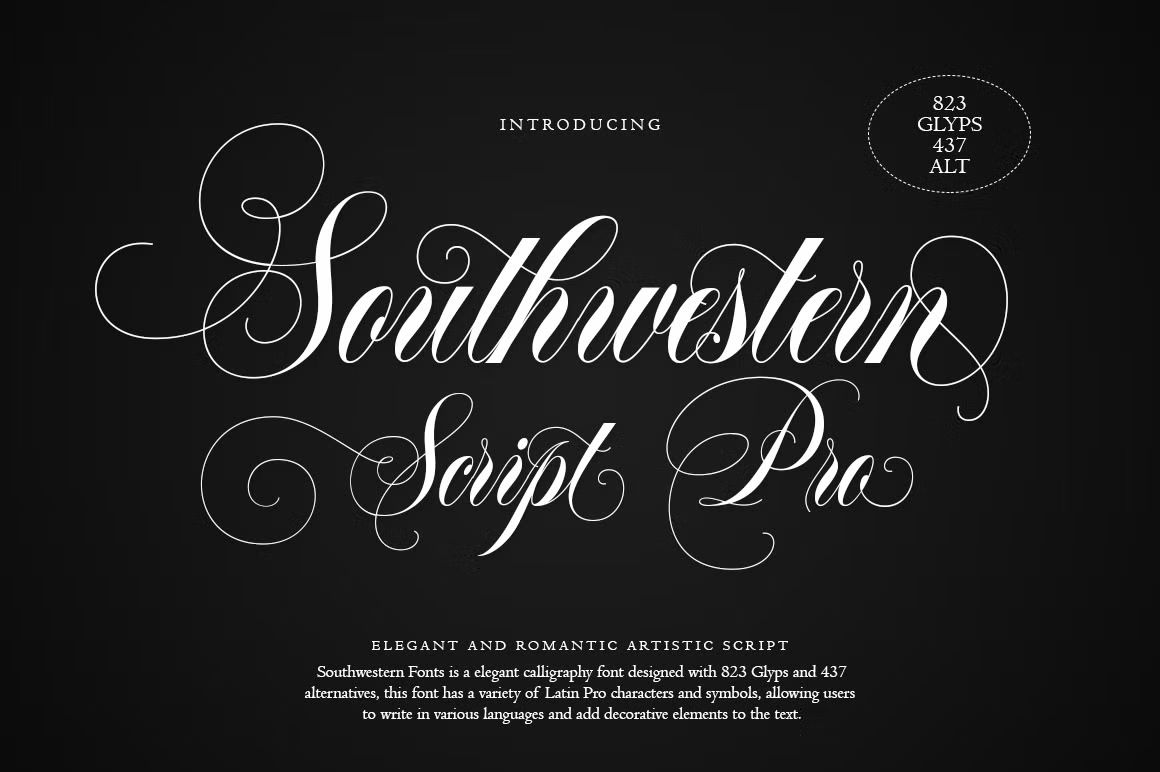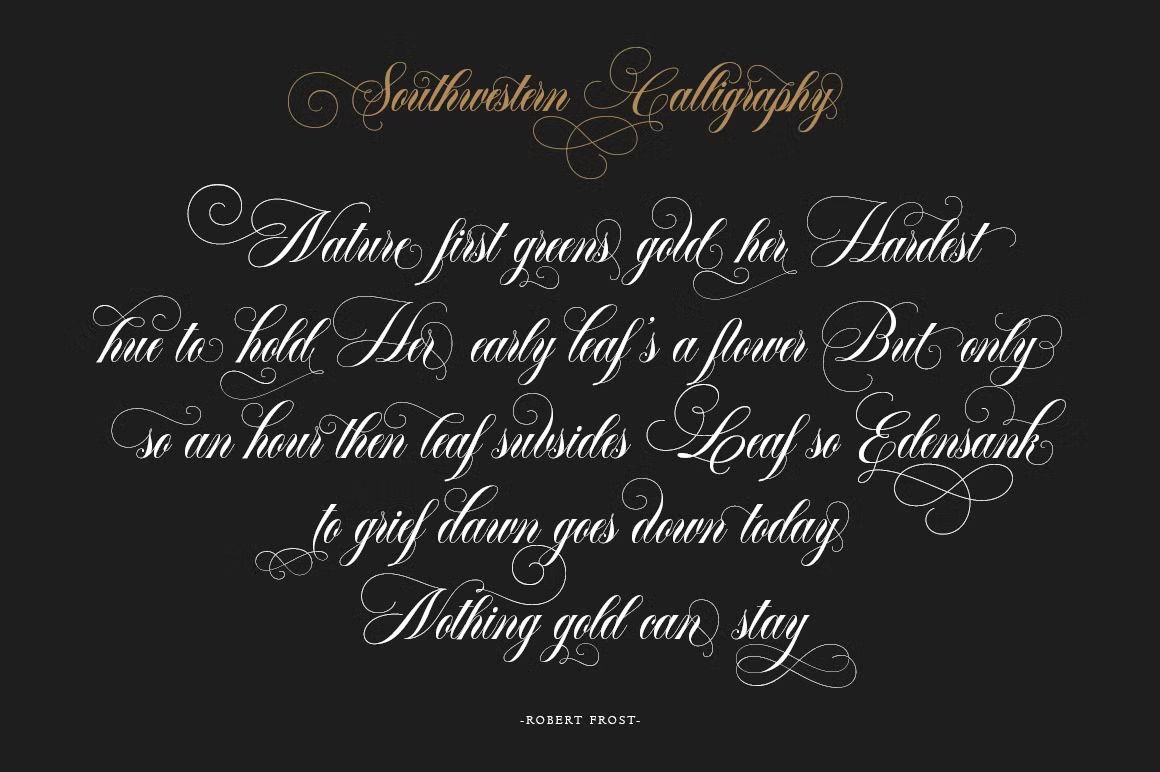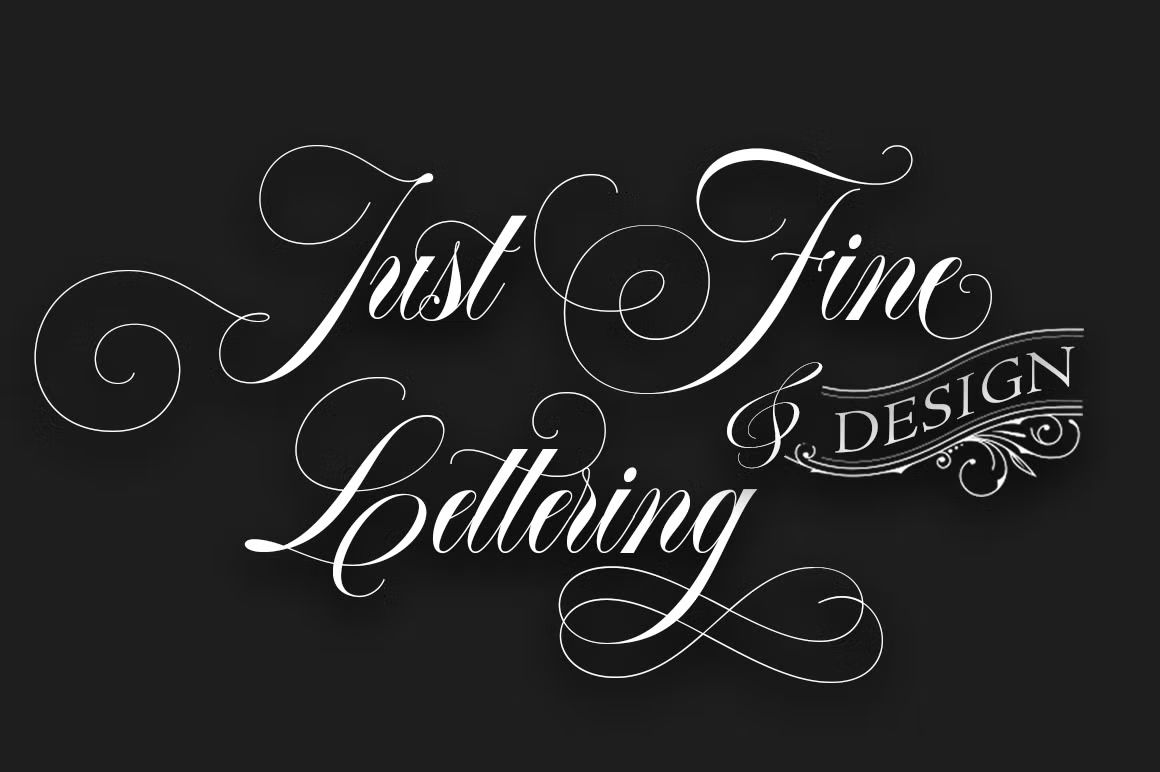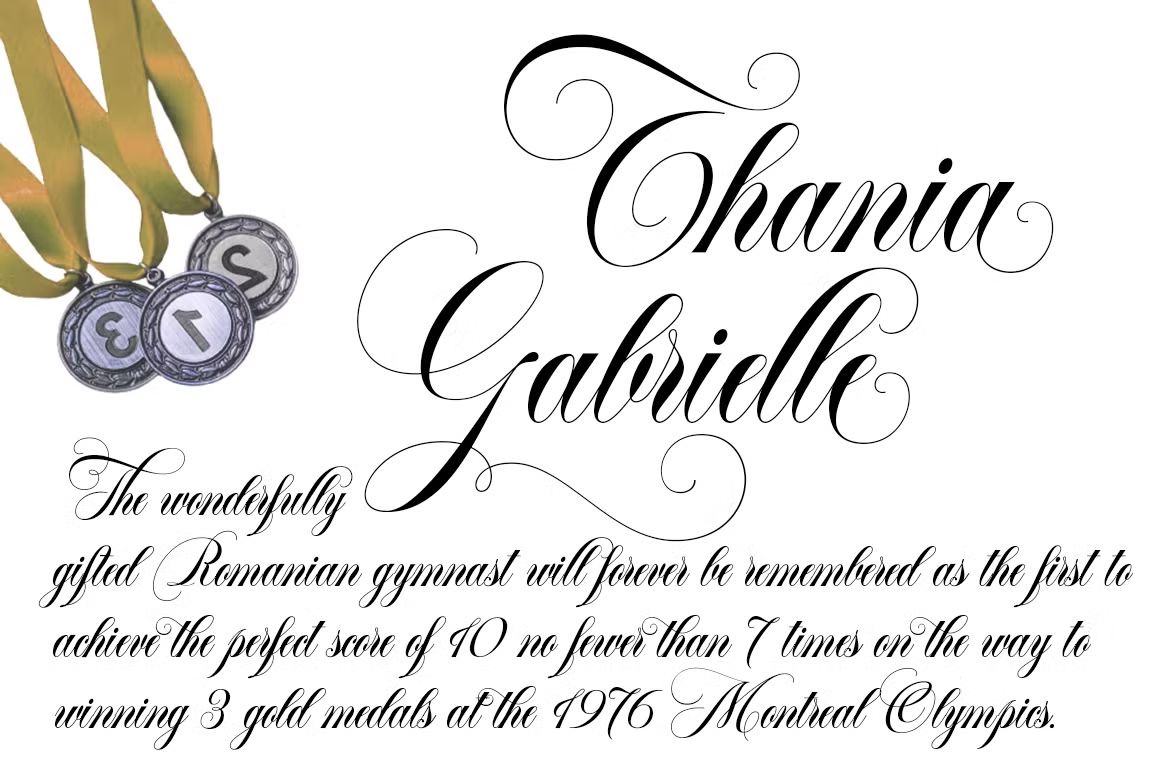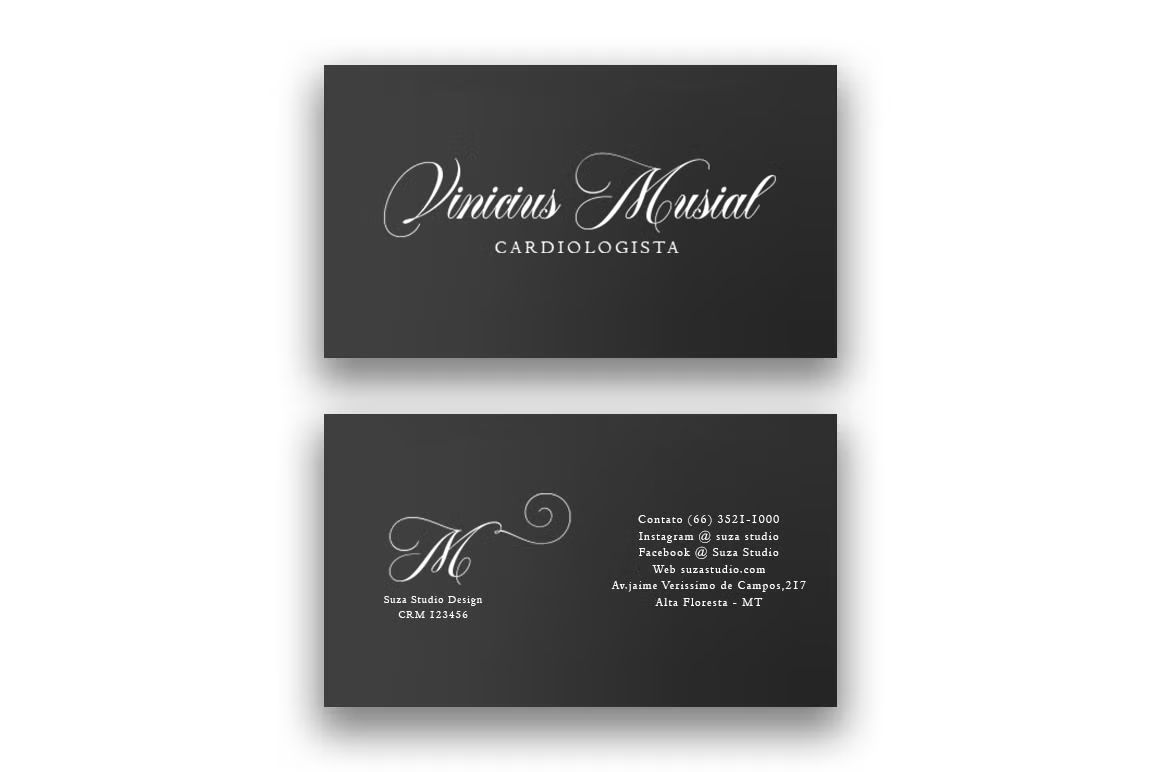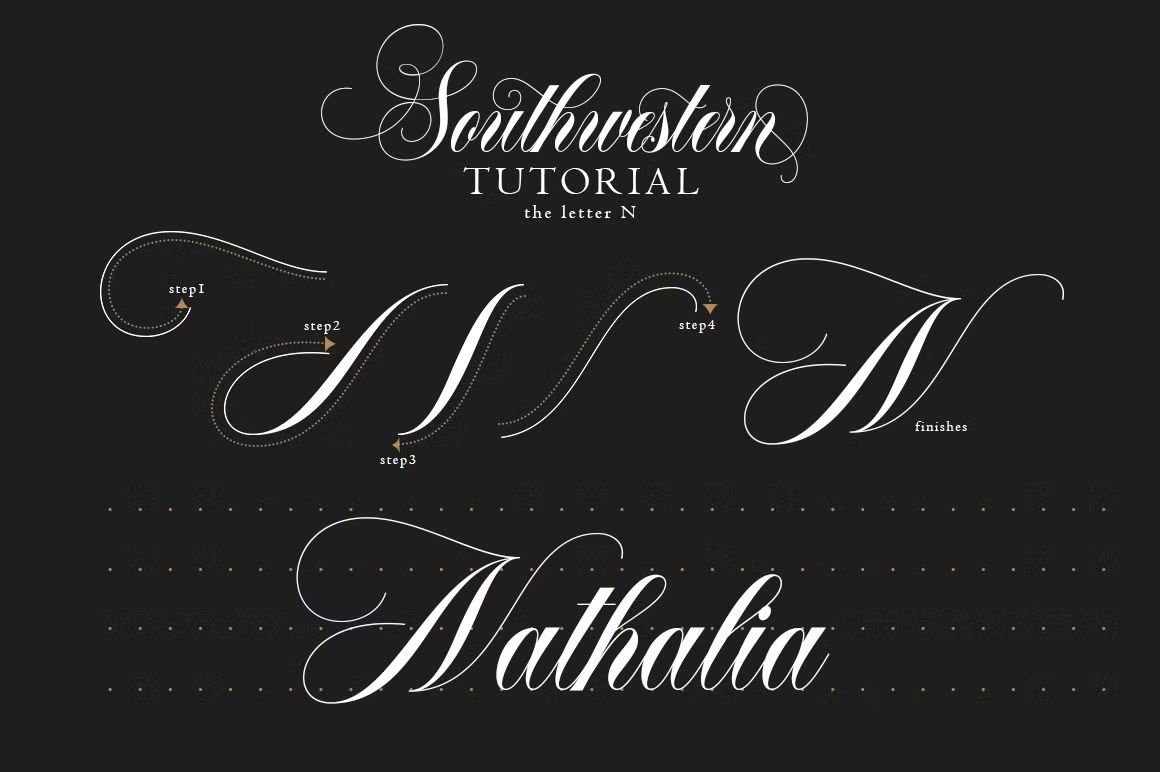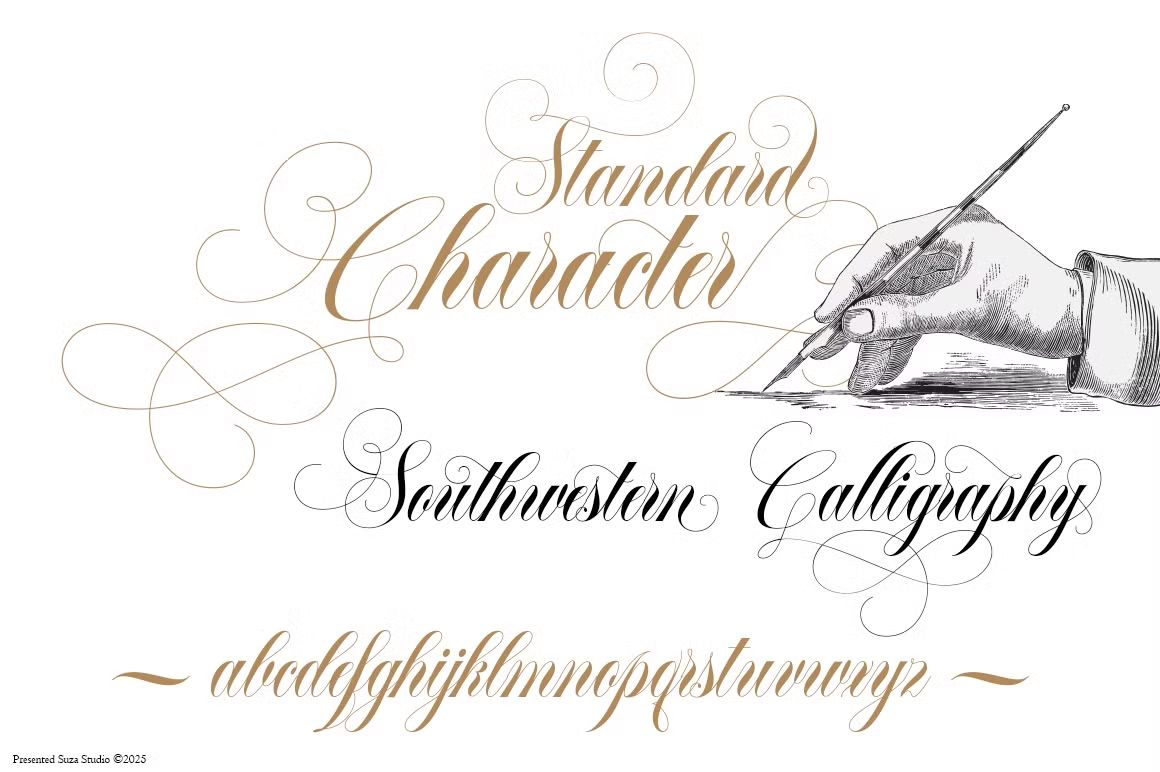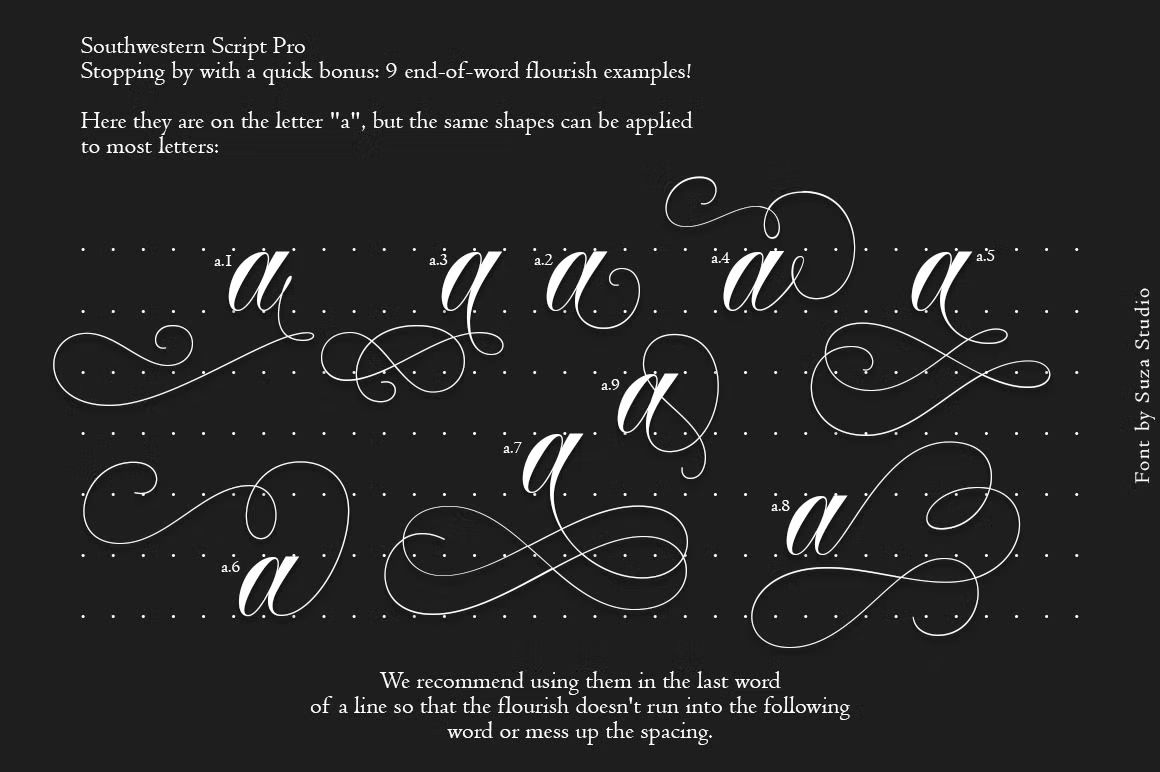
Southwestern – Script Font
Southwestern adalah font script vintage dengan gaya western yang tegas dan berkarakter. Cocok untuk label, poster, dan desain retro. Format OTF/TTF/WOFF, siap digunakan.
Southwestern adalah font script bergaya vintage western dengan sapuan kuas yang tegas dan karakter yang penuh gaya. Font ini cocok untuk desain bertema retro, western, branding rustic, label produk, poster, dan signage dengan sentuhan klasik Amerika. Kombinasi antara garis ekspresif dan detail khas menjadikan Southwestern pilihan ideal untuk desain yang ingin tampil berani dan berkarakter.
• Script vintage dengan nuansa western klasik
• Cocok untuk branding rustic, label, dan signage
• Termasuk huruf besar, kecil, angka, simbol, dan ligatur